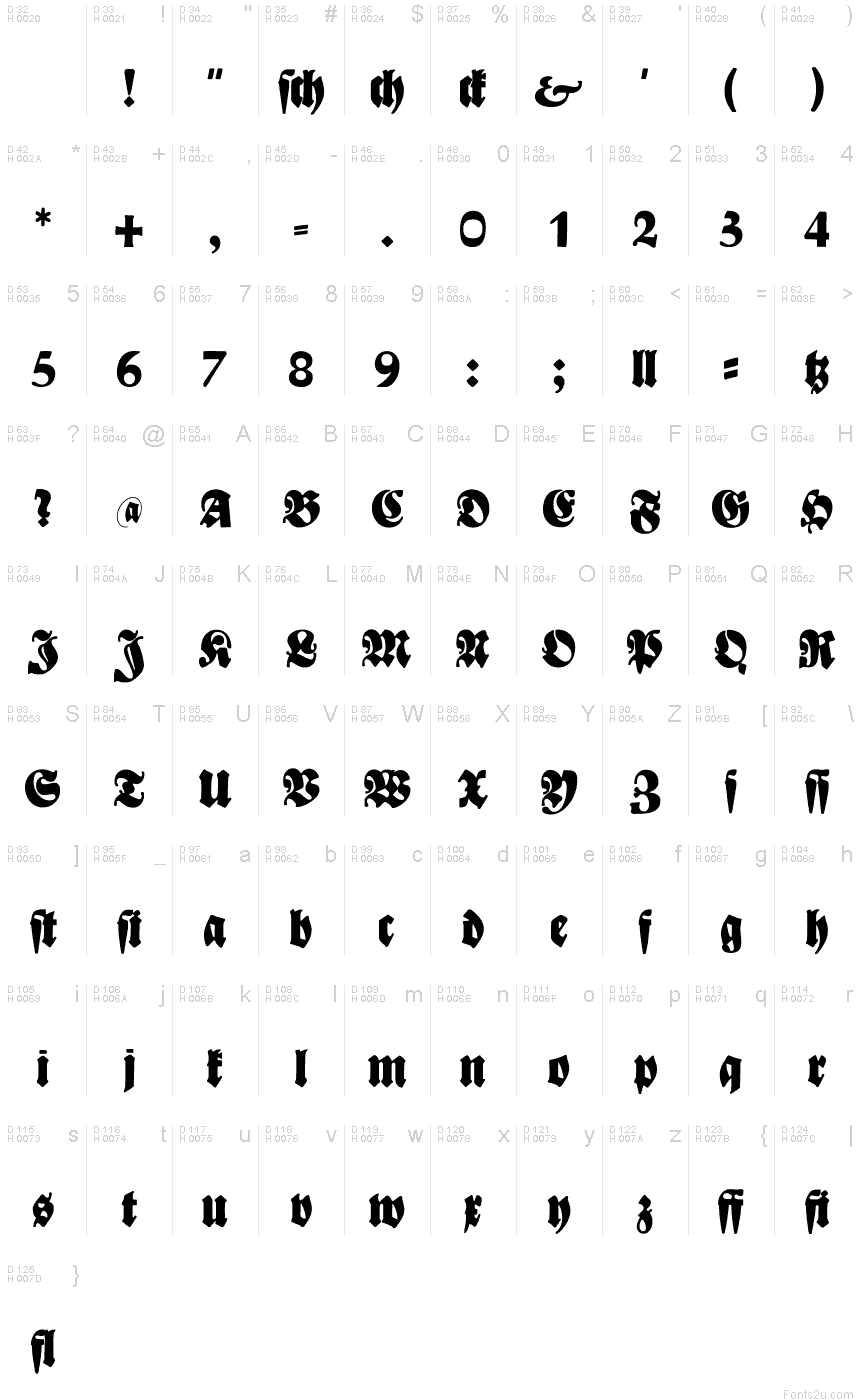
Bayreuth autorstwa Ernsta Schneidlera to darmowy gotycki font, którego gęsty, atramentowy rytm przypomina rzeźbione i tłoczone litery. Odważna waga i ciasny rozstaw tworzą wyrazisty kształt słów, a spiczaste kąty i przełamane łuki nadają całości niepowtarzalnego, starodawnego charakteru.
Wykorzystaj Bayreuth, aby nadać wyrazistości plakatom festiwalowym, etykietom piw i alkoholi, okładkom albumów metalowych i folkowych, książkom fantasy, zaproszeniom na imprezy średniowieczne, brandingowi w stylu tatuażu czy nagłówkom w formie certyfikatów. Użyj dużego rozmiaru i pozwól mu oddychać dzięki szerokim światłom między znakami, a następnie zestaw ten darmowy font ze spokojnym krojem bezszeryfowym, takim jak Futura, lub prostym groteskiem, aby uzyskać czytelny tekst towarzyszący.
Ernst Schneidler fuer C.E.Weber, Stuttgart 1932
Bayreuth